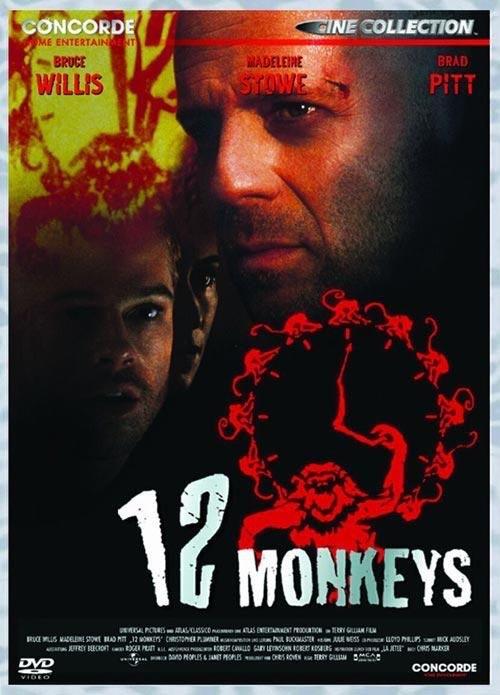
Nicht, dass man dir nicht gerne hilft, mal eine Schrift zu finden, und da ist es egal, ob das jetzt ein Gestalterkollege ist, der mit seiner Arbeit nicht weiter kommt, und so seine Arbeitszeit vertut, um eine Schrift zu finden, die er seinem Kunden kaum berechnen kann, oder on es sich hier um ein reines Hobbyprojekt dreht, aber jetzt alle für Film-Cover verwendeten, und auf vielfache Weise vom Gestalter dieser Cover (Oder Filmplakate) verzerrten Schriften zu suchen, das wird wohl nichts.
Zudem: Gerade für Filme wird oft auch extra eine komplett neue Schrift erfunden. Das ist ja auch eine Aufgabe für Schriftgestalter.
Klar, ganz oft, ganz komplett neue Schriften – Wiederholungen gibt es da so gut wie gar nicht :D
Ich habe weder behauptet, dass immer neue Schriften für einen Film entwickelt werden, und ebensowenig, dass diese Hausschriften dann nicht später auch in weiteren Filmprojekten verwendet werden. Aber es kommt eben doch gerade in der Filmindustrie vor, dass hier auftäge für eine individuelle Schrift vergeben werden, auch um z.B. für eine Serie von Filmen quasi eine Markenidentität zu schaffen, und eben so auch eine Kontrolle über Mechandizing-Artikel zu bekommen, da dann die Schrift vom Film nur Lizenznehmern zur Verfügung steht. Tauchen dann  Fanartikel zum Film mit anderer Schrift (wenn auch ähnlicher) auf, ist es deutlicher, dass es sich hier um eine Markenfälschung handelt.
Das mit der Markenidentität sehe ich ein und ist klar – ob das Thema Kontrolle bei der Vergabe einer Gestaltung so vorrangig gestellt wird wage ich zu bezweifeln.
Hast du gerade mal ein Beispiel für eine individuelle Schrift für einen Film? Also eine komplette Satzschrift, mehr als nur ein Schriftzug, der ja eigentlich auch nur™ ein Logo ist ...
Im Nachhinein sind zu einigen Filmen ja tatsächlich Schriften in Anlehnung an Filmplakate erschienen gebastelt wurden – aber andersrum ...  8-)  :-?
Akut hab ich jetzt grad kein Beispiel parat. Ist halt die Erfahrung über die Jahre, dass mir eben schon Schriften über den Weg gelaufen sind, über die ich dann in irgend einem englischspachigen Forum gelesen habe, dass die verwendete Schrift extra für den Film gestaltet wurde, und eben eine Hausschrift einer der großen Produktionsfirmen sei, und ausschließlich für die Herstellung von Fanartikeln lizensiert werde.
Zudem bin ich mir bei der großen Liste der Trajan, die du genannt hast, nicht sicher, ob da nicht die eine oder andere zur Hausschrift modifizierte Version dazwischen ist, z.B. ein andere a oder g (wenn in der Standardschrift das dreistöckige g drin steckt, eben dann ein doppelstöckoges, und ähnlich beim a)
So etwas merkt man dann, wenn in den Vor- oder Nachspann ergänzungen hinein kommen, wenn der Film syncronisiert wurde, Das Syncronstudio sich zwar größte Mühe gegeben hat, möglichst die Schrift vom Film zu finden, dann aber eine reguläre Version ohne die Modifikationen einsetzt. Das mögen 99% der Filmfans gar nicht wahr nehmen, wenn dann plötzlich in ein paar Namen das e einen waagerechten Strich hat.
Und ja, solche Digitalisierungen Basteleien hab ich ja auch verbrochen :-)
Dass das vorkommt will ich auch gar nicht in Frage stellen, aber ich meine nicht dass es wesentlich in der Filmindustrie ist. Das ist doch z. B. bei Profi-Sport-Trikots weitaus verbreiteter, wie man hier oft sieht.
So selten ist das glaube ich gar nicht. Wenn das Budget groß genug ist, kann man sich ja leicht einen Custom Font für die Titelei und das Marketing leisten. Aber die Kontrolle von Fan-Artikeln ist dann wahrscheinlich eher ein netter Nebeneffekt (der von nachgebastelten Dafont-Fonts schnell wieder kaputtgemacht wird), nicht die eigentliche Motivation.
Das mit den Sport-Trokots stimmt allerdings, und hat dort ja den gleichen Sinn. Drum hanen ja praktisch alle Schriftenhäuser auch eigene Abteilungen zur Erstellung völlig eigenständiger, aber oft auch nur leicht veränderter Hausschriften, Es scheint sich damit ja einiges an Geld machen zu lassen.